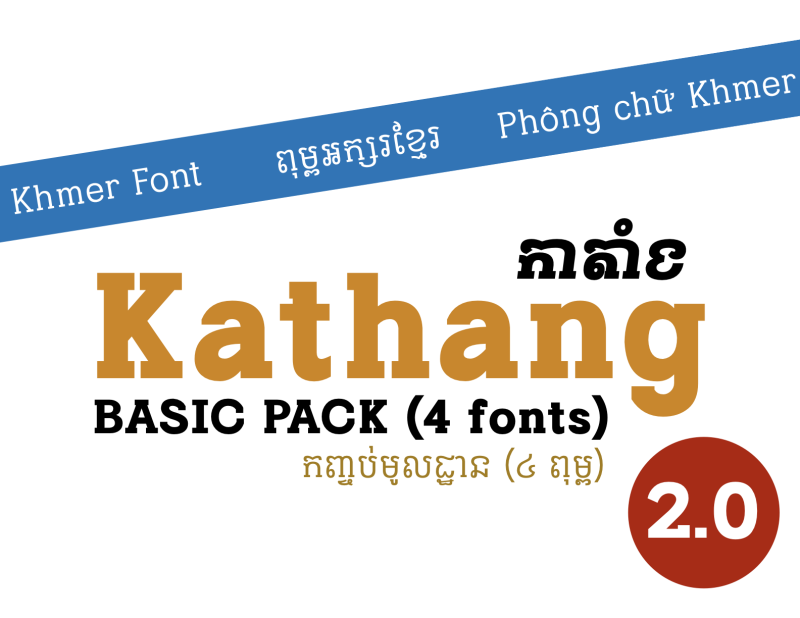
Basic package (4 fonts) product featuring slab serif glyphs and slab serif true italics for the Khmer and Latin script - Regular, Italic, Bold & Bold Italic
ពុម្ពអក្សរខ្មែររចនាបែប អក្សរខម ដែលមានសក់ជាជ្រុងហៅថា Kathang (កាតាំង)។ កញ្ចប់មូលដ្ឋាននេះមានទាំង ធម្មតា ទ្រេត ដិត និង ទ្រេតដិត។
ពុម្ពអក្សរទាំង៤ក្បាលនេះនឹងប្រគល់ឲ្យអ្នកចាប់ផ្ដើមបង្កើតនូវ ក្រហ្វិក ការផ្សាយពាណិជ្ជកម្ម និមិត្តសញ្ញា និង ស្លាកយីហោដ៏ស្រស់ស្អាត ដែលសមស្របជាអក្សរធំបង្ហាញ ឬក៏អក្សរក្នុងអត្ថបទ។
[កញ្ចប់ពុម្ពអក្សរនេះមានបួន (៤) ពុម្ពអក្សរនៃ គ្រូសារពុម្ពអក្សរ Kathang - ធម្មតា ទ្រេត ដិត និង ទ្រេតដិត]
អក្សរទាន់សម័យមែន តើនៅតែគោរពដល់អក្សរជាតិដូនតាយើង Kathang Pro នាំអក្សរបុរាណមកប្រើលើកុំព្យូទ័រទំនើប។
Kathang, the slab serif Kham-script Khmer typeface. This basic pack contains Regular, Italic, Bold and Bold Italic.
THESE 4 FONT styles will enable you get started on creating beautiful graphics, advertisements, logos, and banners that is ideal for Display and Text.
[THIS PACK FEATURES FOUR (4) KATHANG FONTS - REGULAR, ITALIC, BOLD & BOLD ITALIC]
Modern yet paying homage to our ancestral script, Kathang Pro brings our ancient letters to modern computers.